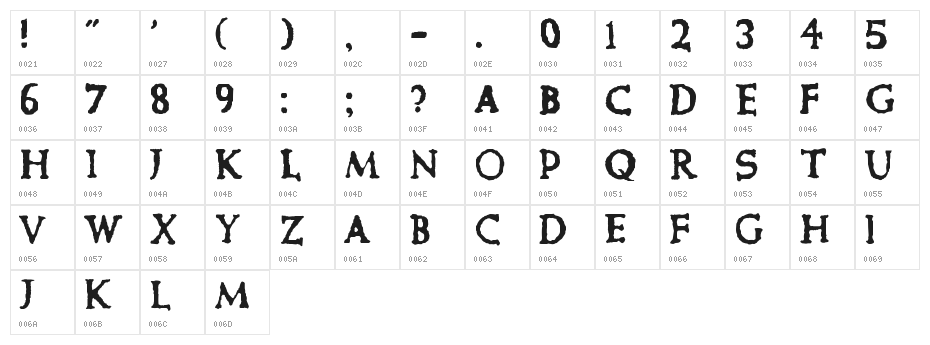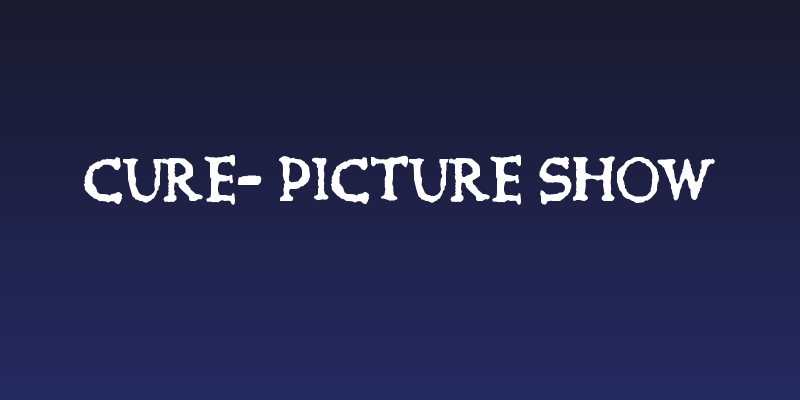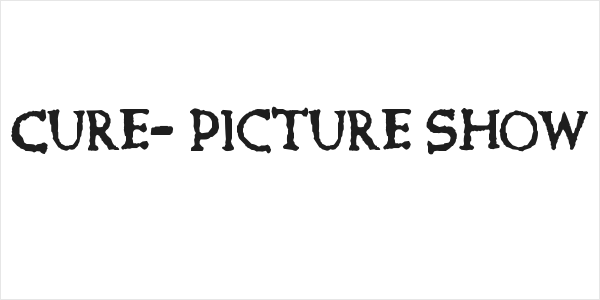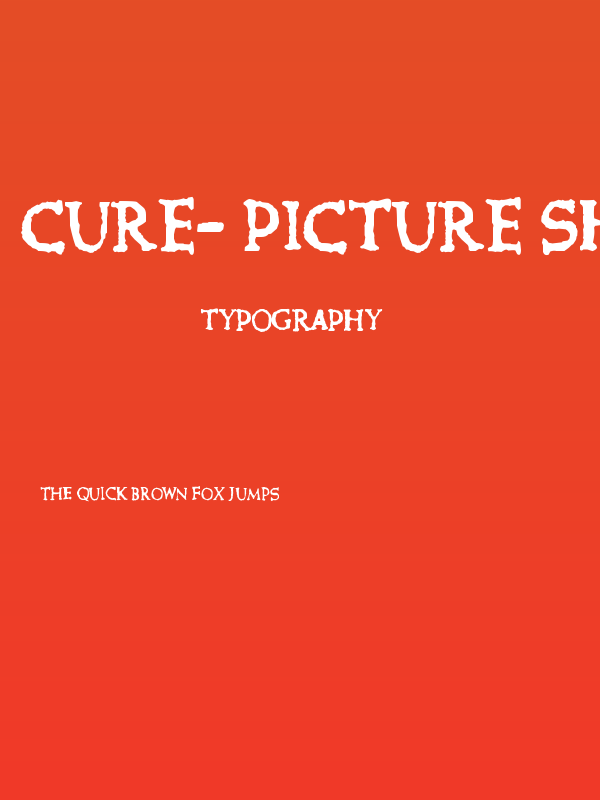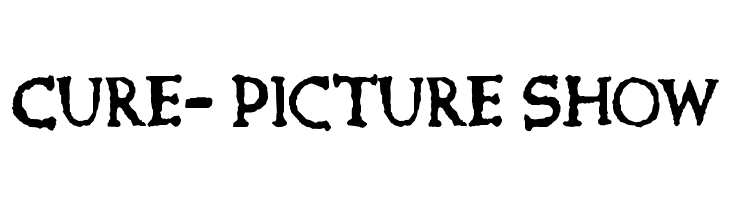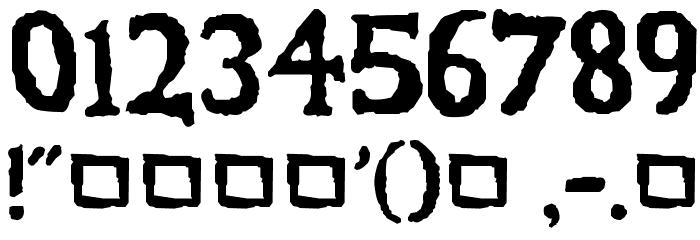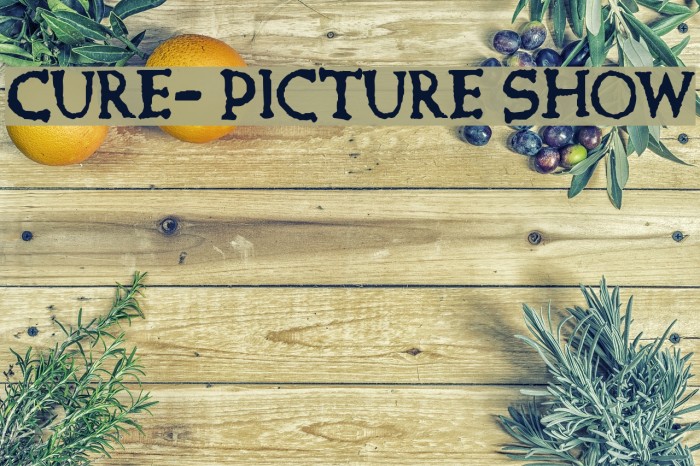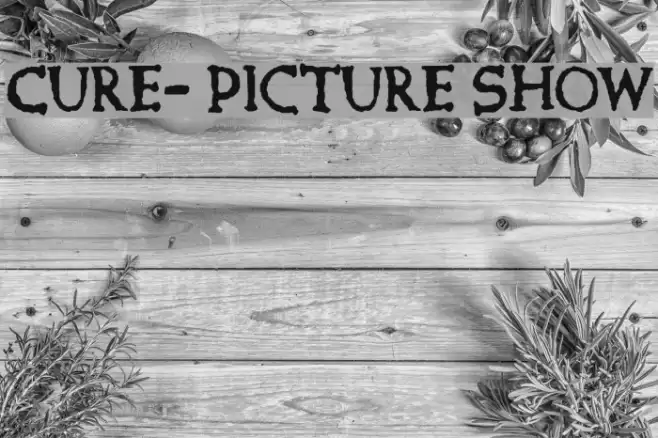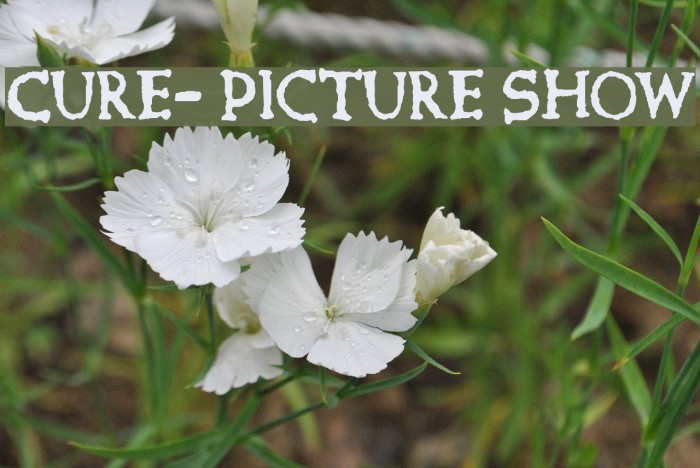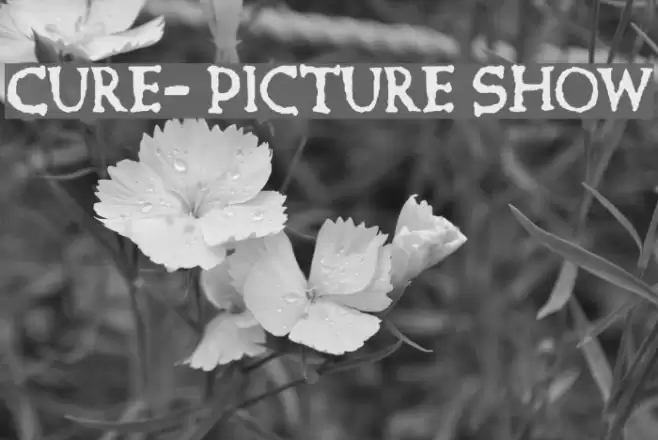
Cure- Picture Show Font
| Progetti proposti | Ideal for vintage posters, retro-themed designs, branding for artisanal products, and any project seeking a handcrafted or nostalgic look. |